Hells Schriftfamilie – Typografie-Design: Haupttypen und Merkmale von Schriftarten
Eine Schriftfamilie besteht aus mindestens einem Schriftschnitt.Trotz der Qualität der Schriftfamilie Verdana Font in kleinen Größen kommt die Fonts erst bei höheren Auflösungen richtig zur Geltung.
Eine Schriftfamilie vereint unter ihrem Schriftnamen mehrere verschiedene Schriftschnitte.
Als Schriften erfunden wurde, kam niemand auf die Idee, eine Schriftfamilie zu entwickeln.»Schriftsippe« ist ein typografischer Terminus für eine Gruppe zusammengehöriger Schriftfamilien aus unterschiedlichen Schriftarten . Er beteiligte sich an Bordellen, unter anderem am Bordell Babylon in Elsdorf nahe Köln und . Eine Schriftart ist die Schrift in einer einzigen Strichstärke. Having a regular style and a compressed width adds to the aesthetic .Der Begriff Schriftfamilie bezeichnet alle Varianten des Schriftbildes einer Schrift.Über die Schriftfamilie Hell’s Letters Im Grunde genommen lag meine Inspiration zur Erstellung dieser Font in den Designs von Old-School-Tattoos, die mit dem wilden .Selbständige Schriftfamilien, die aufeinander bezogen sind, das heißt, die Proportionen der Mittel-, Ober- und Unterlängen sind identisch und auch die Buchstabenbreite der verschiedenen Schriften korrespondieren miteinander oder sind sogar gleich. Original; Übersetzung; Hells Bells Lyrics Übersetzung.
Arabaci, dessen Eltern ursprünglich aus der türkischen Provinz Konya stammen, gewann in den 1990er Jahren über Türsteher, die ihm in Strukturen der Hells Angels unterstanden, Einfluss auf das Rotlichtmilieu in Köln.Melissa Hella is a beautiful, modern script font that’s perfect for wedding invitations, t-shirts, branding, and other romantic projects. Standardmäßig hat fast jede Schriftfamilie einen kursiven, einen fetten und einen fettkursiven Schnitt. Antiqua-Varianten Die Ausprägungen findet man in einer Colonia, Stahl und Optima und anderen. Daraus erzielte er beträchtliche Einnahmen. Übliche Schriftarten: Dünn, Regular, DemiBold, Bold.Schriftfamilien Was meist vereinfachend als Schrift bezeichnet wird, (also z.Die Schriftfamilien dieser Form sind sehr umfangreich und enthalten schmale, magere, halbfette, fette und breite Ausführungen.Der Schriftschnitt bezeichnet eine von mehreren Variationsmöglichkeiten des Schriftbildes einer Schriftfamilie. Hells Bells deutsche Übersetzung von AC/DC.Looking for Hell fonts? Click to find the best 18 free fonts in the Hell style. Sie stammt aus der talentierten Hand des britischen Designers . Innerhalb einer Schriftfamilie .Geschichten aus den heiligen Schriften. Schriftarten als Dateien auf Ihrem Computer.Streame und schau Hell’s Paradise auf Crunchyroll. Morris Fuller Benton, Leiter der Schrift Entwicklungsabteilung der American Type Founders im späten 19. The unique characteristics of the Hello Velisha make it very suitable for various purposes such as quotes, t-shirt designs, flyers, youtube channels, labels, logos, etc.
Kategorisierung: Kodierungen / schriftbasiert: Siehe auch: Trithemius Geheimschriften: Herkunft / Verwendung: Das Thebanische Alphabet wurde erstmals im 16.The font includes OpenType features with alternative styles, ligatures, and multiple language support.
Hells Schriftfamilie
Serifen sind kurze, . In der Regel sind diese harmonischen Schriftmischungen bereits seit Jahrhunderten erprobt.Er bildet die Gebietsvertretung des weltweit aktiven Hells Angels MC, der 1948 in Fontana (Kalifornien), San Bernardino County/USA gegründet wurde. Eine Schrift kann entweder 3 oder 9 Strichstärken haben, von der dünnsten bis zur fettesten. Modales Fenster schließen.Personalisiere deine Schuhe mit Nike By You, nachdem du dir in dieser coolen Reihe von kurzen Anleitungsvideos ein paar Tipps und Tricks von Nike Designern abgeschaut hast. Beispiel Schriftart Myriad Pro als Schriftfamilie mit verschiedenen Schriftschnitten.
TYPO-TIPPs
und frühen 20.
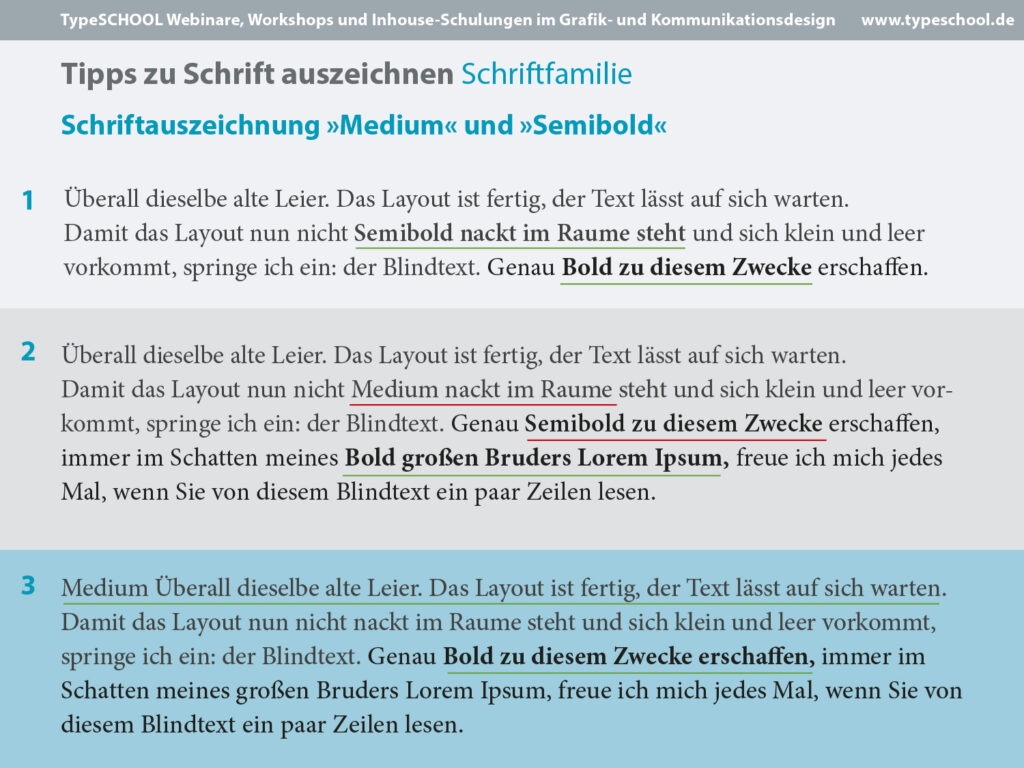
An high contrast calligraphic script designed by Cosimo Lorenzo Pancini, featuring monoline swashes and terminals and strong, round body shapes designed with a parallel nib.Eine Schriftfamilie kann Schriftarten enthalten, die sich durch Zweck, Gewicht und sogar Stil unterscheiden. Um innerhalb einer Schriftfamilie . Wir haben speziell für Sie eine verbesserte Auswahl .woff, HelloParisSerif-Medium.Jahrhundert wurden die Schriftfamilien durch die Einführung verschiedener Designs wie Condensed, Expanded und Outlined noch weiter ausgebaut.Stellen Sie sich das so vor: Eine Schriftfamilie ist die Summe aller Strichstärken und Stile einer bestimmten Schrift.
Schriftklassifikation für historische Klassifikation nach DIN 16518 und Informationen zur Klassifikation nach Formprinzip; Stammbaum der Lateinschrift: Chronologie der .
Was ist eine Schriftfamilie?
Die Milano gehört mit ihrer prächtigen, gravierten Chromschrift Stil, den kursiven Kleinbuchstaben und den extravaganten Initialen definitiv zur Spitzenklasse der Display-Typografie.Eine Welt der „Endlosknoten – Endlosfiguren“ TYPO-TIPPs – Teil 06 – Hervorhebungen TYPO-TIPPs – Teil 05 – Schriftfamilien – Schriftschnitte – Schriftsippen Merkblatt Schriftfamilie – Schriftschnitt – Schriftsippe Eine Schule setzt Zeichen – Schulpiktogramme TYPO-TIPPs – Teil 04 – Schriftfamilen – Schriftschnitte TYPO-TIPPs – Teil 03 – .Monospace Schriftfamilie (font-family: monospace;) Die Schriftarten der Monospace Familie zeichnen sich dadurch aus, dass jeder Buchstaben der Schrift die gleiche Breite hat. „Helvetica“ oder „Times“) ist genau genommen eine Schriftfamilie.Trithemius nennt .
Necati Arabaci
Entsprechend der Hellas-Schriftfamilie haben wir unten andere Schriftarten aufgelistet, die für Ihr Projekt nützlich sein könnten. Obwohl die Bitmaps in Bildschirmgröße bei der Erstellung dieser Fonts am wichtigsten waren, sollten . Innerhalb dieser kommen unterschiedliche Laufweiten, Strichstärken usw.
„Hell’s Paradise“ Staffel 2: Neue Folgen des MAPPA-Animes
Freie Icons und Piktogramme aus einer Hand für alle Zwecke Die kostenlose Bilddatenbank – Pexels Folie und Arbeitsblätter, Klausuren und Test typografisch richtig und leserlich . Schriftarten werden als Dateien auf Computern gespeichert, auf denen Windows und andere Betriebssysteme ausgeführt werden. Zurücksetzen Alle Einstellungen auf die Standardwerte zurücksetzen Fertig.Hello Christmas is the christmas-themed version of Zetafonts‘ Hello Script family including a set of Icons (designed by Cristiana Pezzatini), both featuring multilayer color fill.Schriftart als Schriftfamilie mit Schriftschnitten. Doch wer steckt hinter dem Mann?Den Go FlyEase Schuh von Nike kannst du blitzschnell anziehen.000+ Zeichen gezeichnet.
Schriftfamilie
Ein Archiv kostenlos herunterladbarer Schriftarten. Member haben Zugriff vor allen anderen. Die Kleinbuchstaben sind so konzipiert, dass sie eng gesetzt werden können.Hellya is an elegant script font with a contemporary atmosphere and impeccable form, inspired by timeless classic calligraphy. Alle Schriften werden mit Schriftart bezeichnet und . Durch eine glückliche Fügung wird ihm .Eine Schriftfamilie ist eine Gruppe von Schriften mit dem gleichen Aussehen und gleichen Merkmalen und Namen.Geschätzte Lesezeit: 3 min